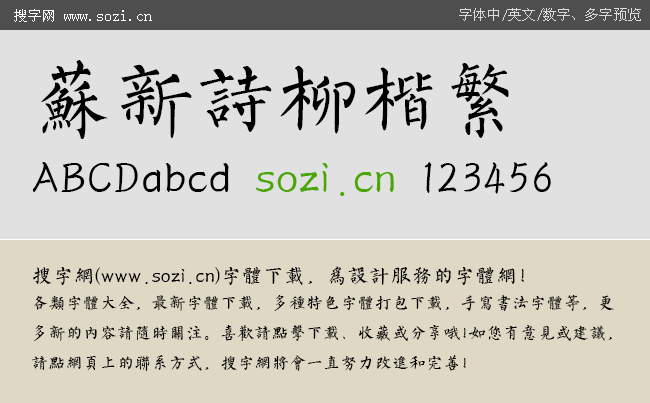
蘇新詩(shī)柳楷繁
搜字網(wǎng)為大家提供一款蘇新詩(shī)柳楷繁書(shū)法字體下載,蘇新詩(shī)柳楷繁是一款手寫(xiě)楷體書(shū)法字體,字形大方美觀,筆畫(huà)棱角分明,可以應(yīng)用于平面廣告、名家題字、 藝術(shù)繪畫(huà)等領(lǐng)域,喜歡的用戶可下載收藏。